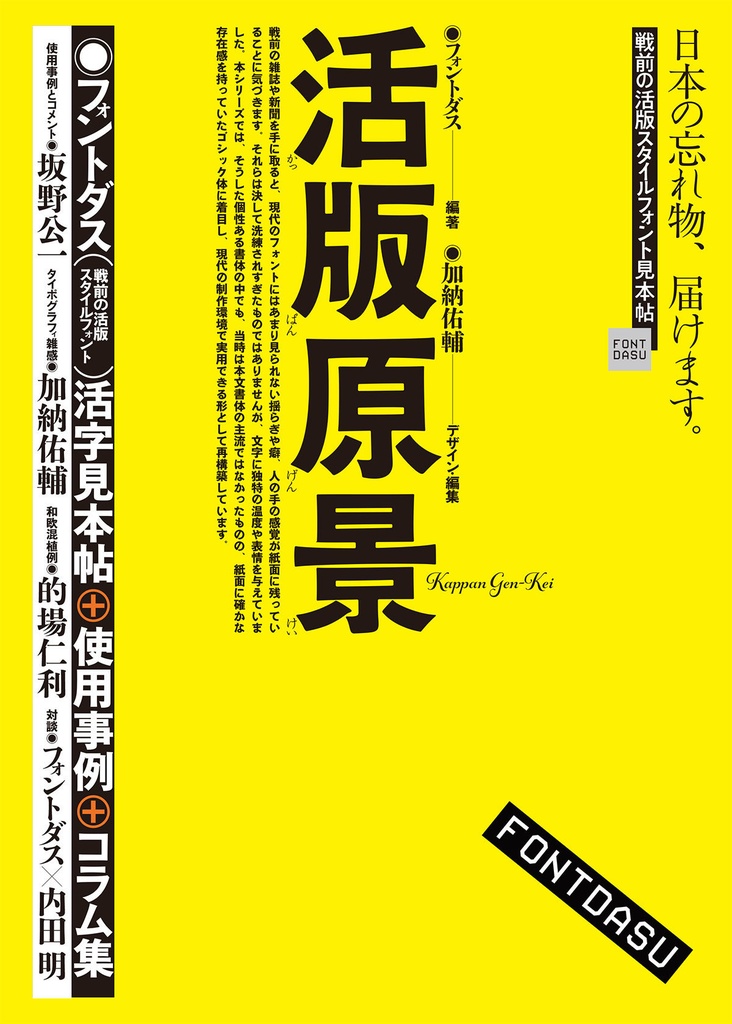
活版原景|戦前活版スタイルフォント見本帖【紙版(冊子)】
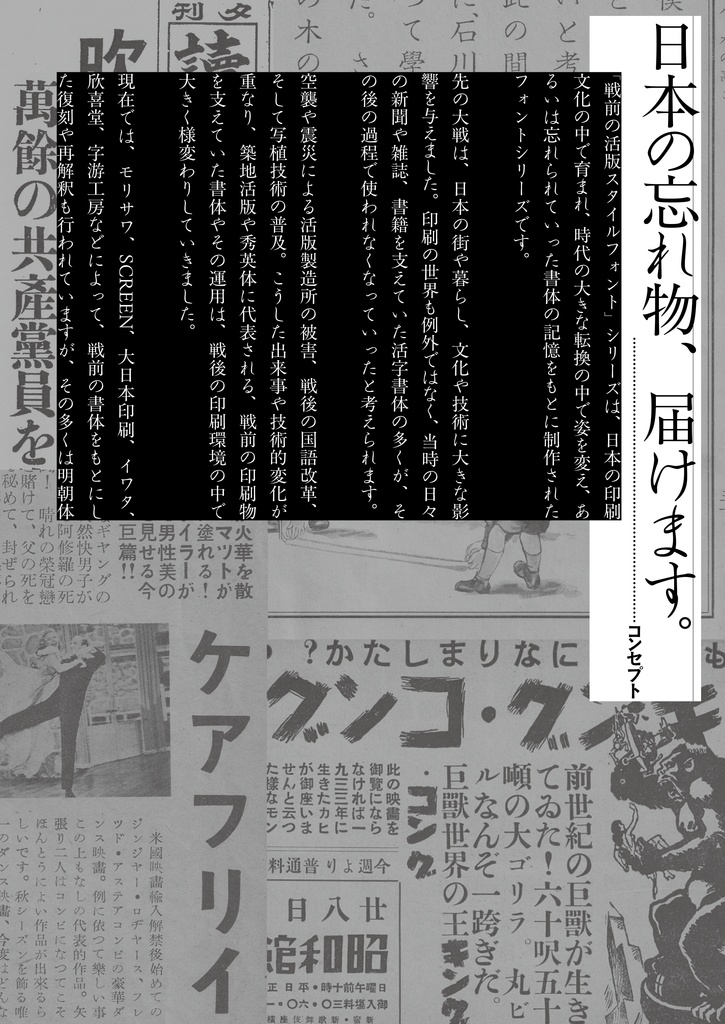
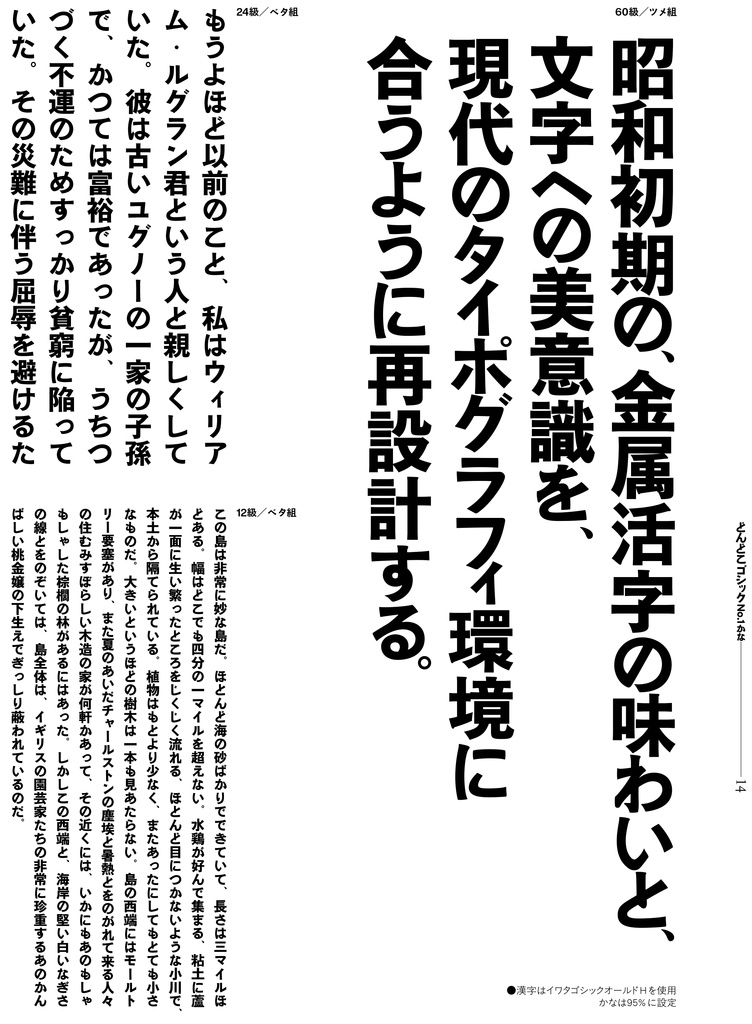
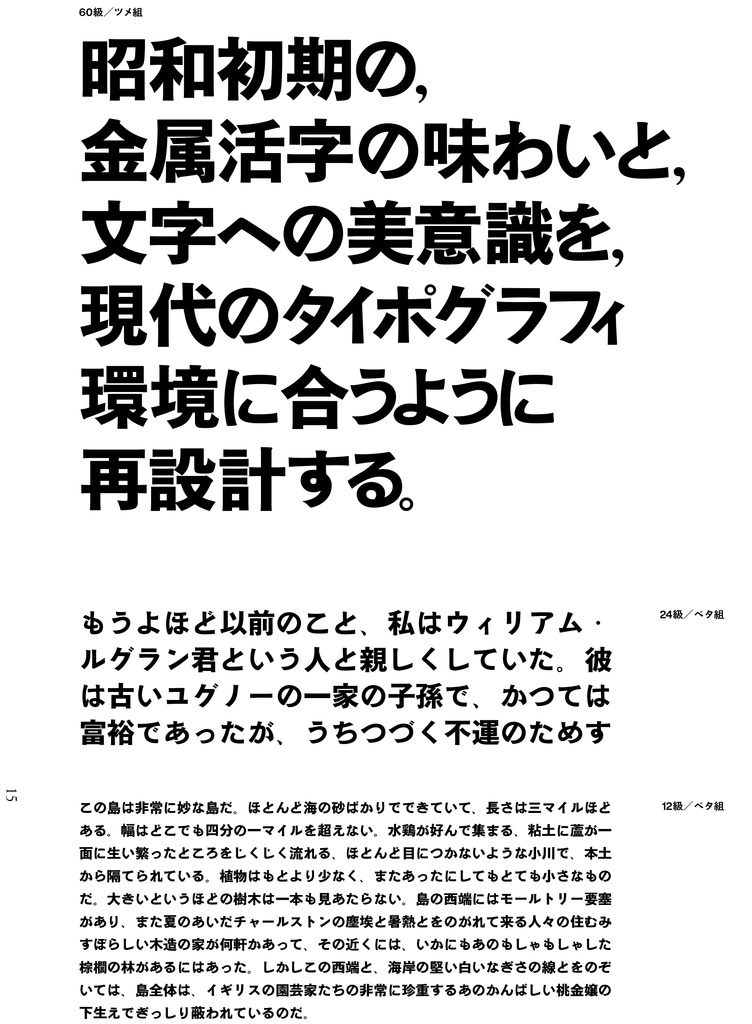
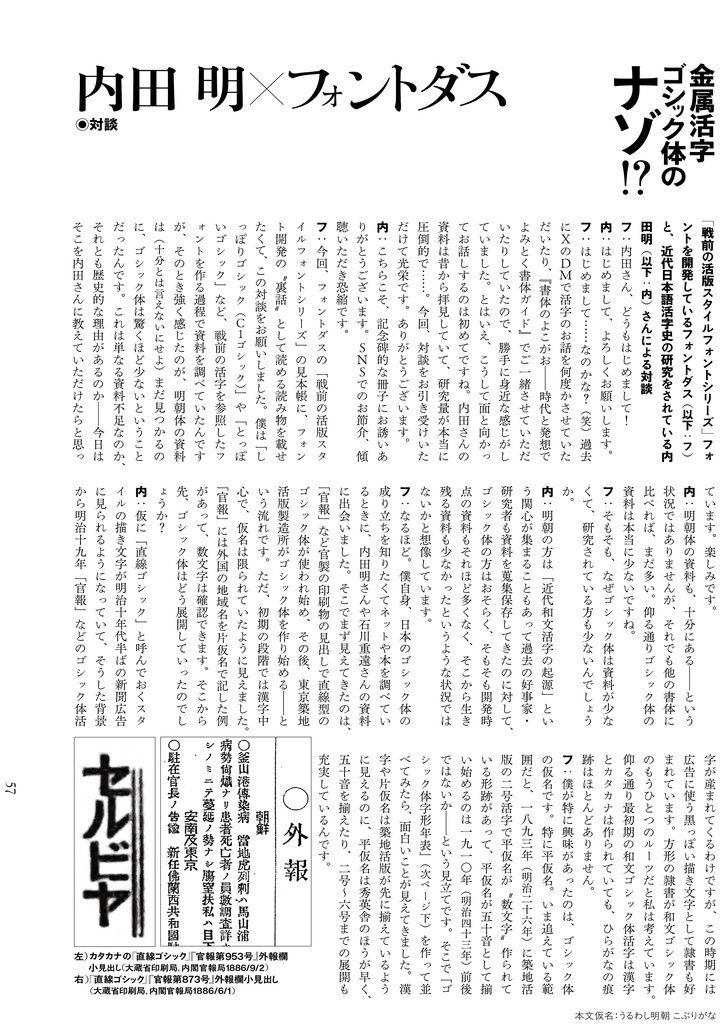
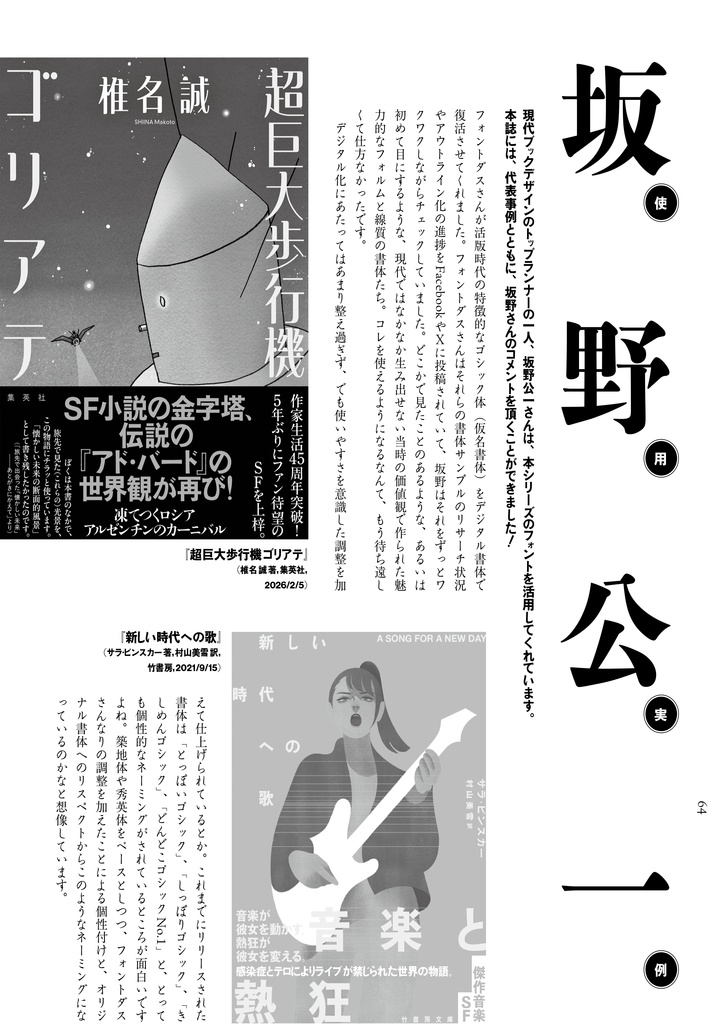
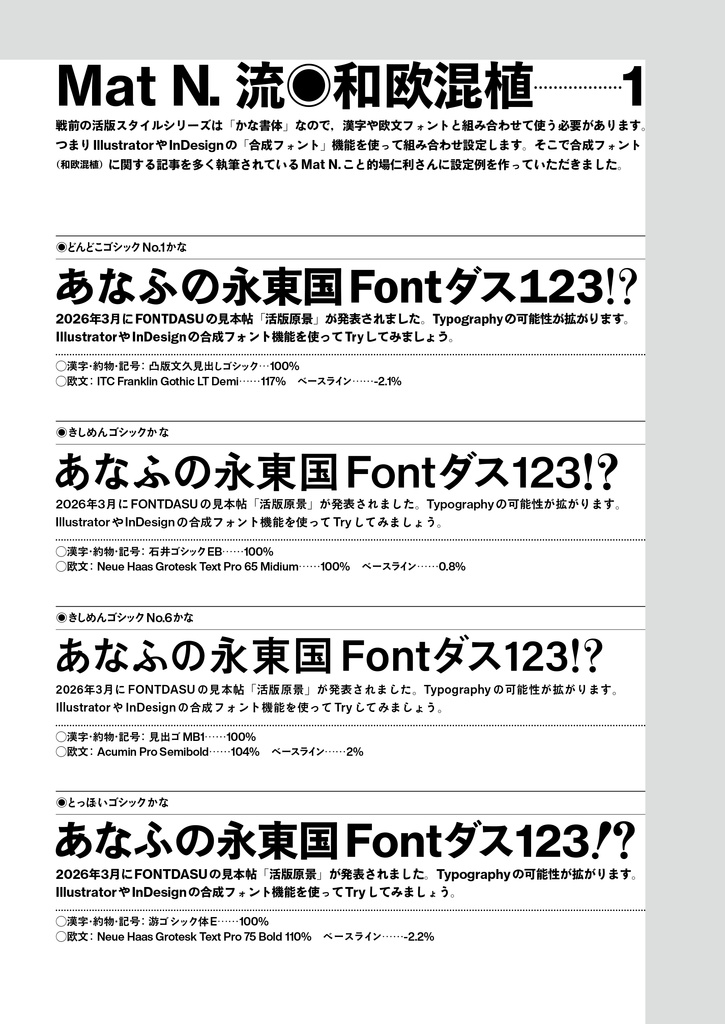
期間限定にょにょゴシックかなお試し版(異体字、B1版、TTF版がない以外製品版と同じです)付 忘れられた活字の景色を、届けに来ました。 『活版原景』は、フォントダスが制作する 「戦前の活版スタイル」フォントシリーズの見本帳です。 字形だけでなく、背景・資料・使い方まで含め、 “読むためのフォント見本帳”として制作しています。 【収録内容】 ・フォント組版見本(縦組/横組) ・装幀家 坂野公一さんによる使用事例+コメント ・活字史研究者 内田明さんとの対談(戦前ゴシック体史) ・元ネタ資料/開発裏話 ・混植例(的場仁利) ・編集/デザイン:加納佑輔 【商品タイプ】 ■ 紙版(冊子) 実際の紙と印刷で楽しむ見本帳です。 活版のニュアンスや組版の空気を、紙面で確認できます。 【仕様】 ・サイズ:B5 ・ページ数:約68ページ ・表紙:表面カラー印刷/中面:モノクロ印刷 【注意】 ・本商品は書籍です。フォントデータは付属しません。